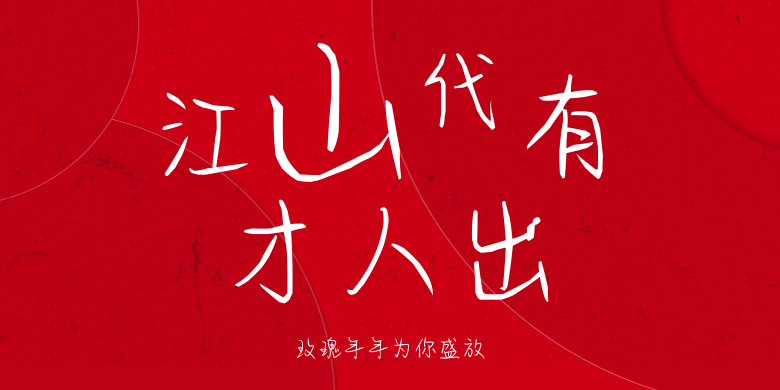
玫瑰年年为你盛放
玫瑰年年为你盛放,这款字体结构工整、笔画清晰,兼顾美观与易读性,适用于标题、正文、海报、包装、LOGO 等多种场景。字形优雅稳定,风格百搭耐看,适配日常排版与创意设计,让文字呈现更舒适、更具质感。玫瑰年年为你盛放一笔一画,皆是细节,以均衡的比例、流畅的线条打造舒适视觉体验,字形端正大气,风格简约现代。无论是商业设计、品牌宣传还是日常排版,都能轻松驾驭,让文字更有格调与力量。玫瑰年年为你盛放字体下载。